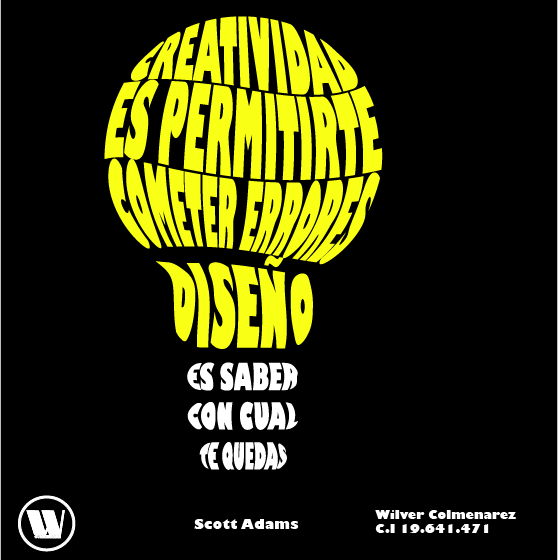
Tipografía / Composición Tipográfica
Se le da este nombre a la composición que permite realizar estructuras gráficas a las letras y que salen fuera de sus normas formales, sus estructuras suelen ser un poco complejas ya que esta pierde todo su contenido semántico ósea su signo lingüístico para pasar al gráfico, la palabra adecuada seria que se des contextualiza ya que abandona su funcionalidad para unirse a otros elemento por los cuales puede ser capaz de transmitir conceptos.
Tipografía en textos
La tipografía en textos nos permite obtener una fuente adecuada y un tamaño de las letras por medio de las cuales se quiere trasmitir un mensaje, también se le hace referencia que cuando hablamos de la tipografía es por medio de un carácter (una letra determinada), para poder definir las letras o la fuente que se utilizara se debe seleccionar por medio de las diferentes fuentes de tipografía que existen, por ejemplo están las egipcias, góticas, modernas entre otras… dentro de estos grupos se encuentran las tipografías: serif, sans serif, script, graphic y monospace, que son las que nos dan la fuente exacta que queramos utilizar.